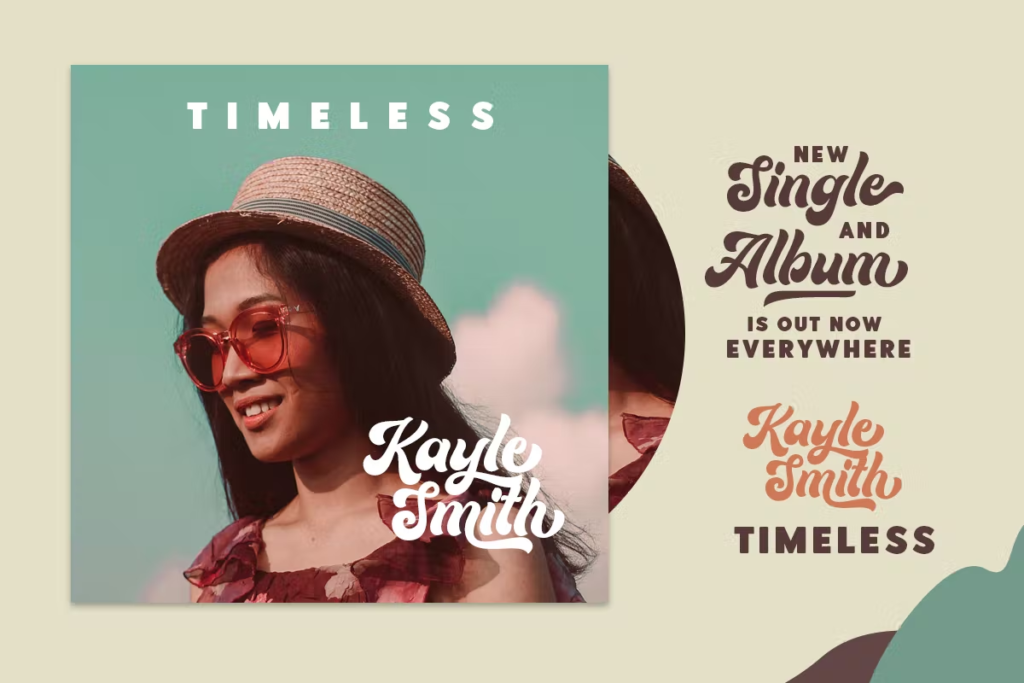
Sucillia Font
Sucillia est une police d’écriture cursive et rayonnante. Raffinée et délicate, cette police rendra chacune de vos créations magnifique. Sucillia est codée en PUA, ce qui signifie que vous pouvez accéder facilement à tous les glyphes et swash !